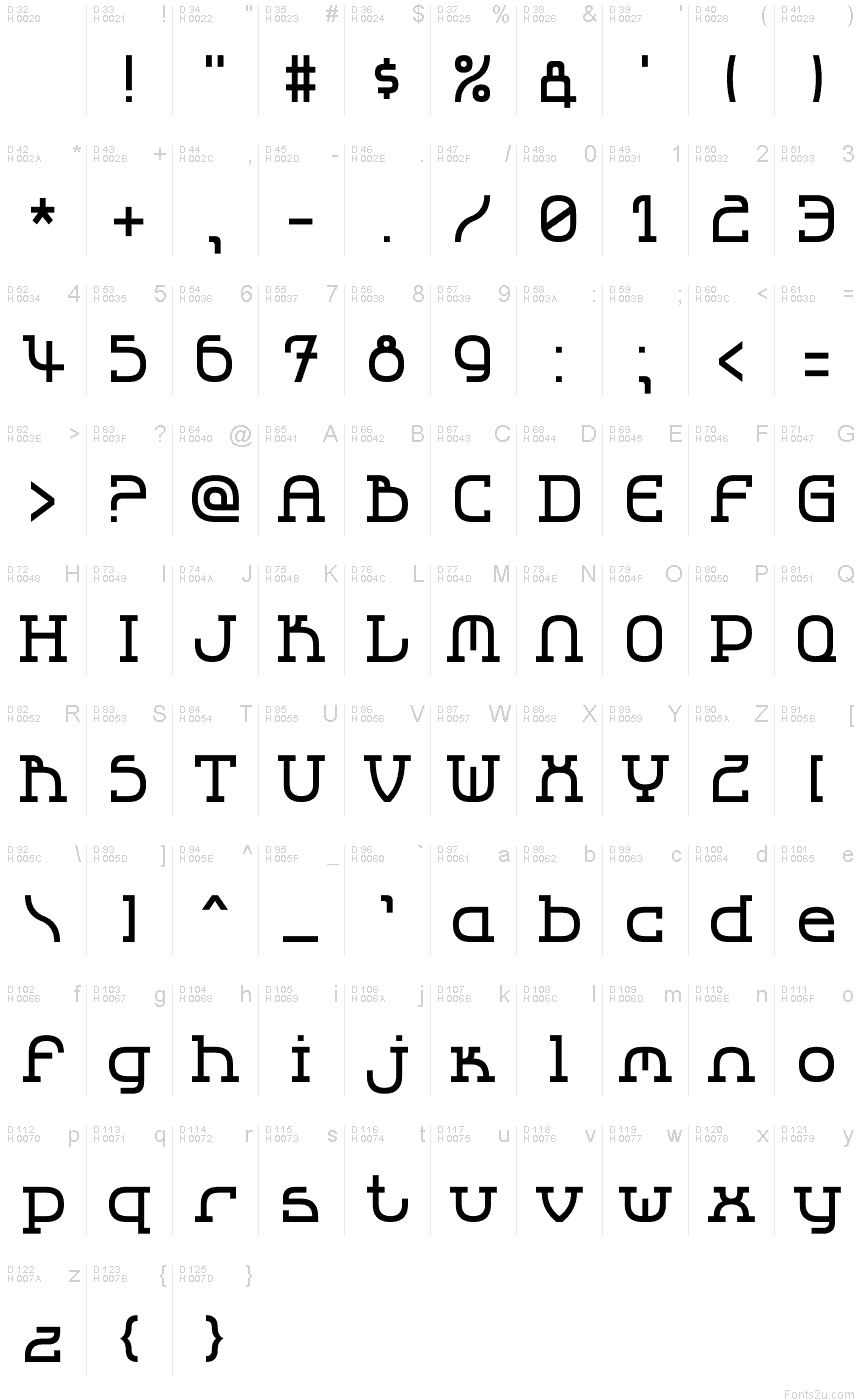
LBC Cool od LBC Computers to darmowy, utrzymany w stylu retro font typu display, oddający klimat popu z przełomu lat 60. i 70. Litery łączą w sobie ostre, poziome cięcia z szerokimi, obłymi krzywiznami, co nadaje krojowi miękki, wyrazisty rytm – jest zabawny, ale nie trąci kiczem.
Doskonale sprawdza się w projektach plakatów, wizerunku marek nawiązujących do muzycznych klimatów, menu kawiarnianych, tytułach na okładkach magazynów, opakowaniach czy planszach tytułowych, gdzie krótkie hasło potrafi zdefiniować styl. Jako darmowy font świetnie nadaje się również do logotypów, monogramów i dużych inicjałów, ponieważ zaokrąglone kształty i kompaktowe łączenia nadają nawet kilku literom wyraźnie „epokowy” charakter.